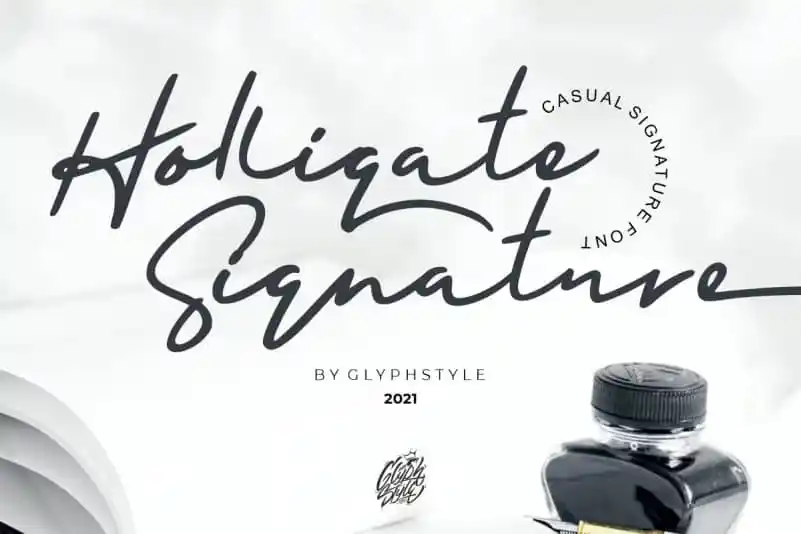
Holligate Signature Font – Fonte Grátis
Holligate Signature Font
A Holligate Signature Font é uma letra que desvenda a espiritualidade dos autógrafos relaxados e naturais. Suave e elegante, essa fonte traz uma sensação quase mágica de autenticidade à sua identidade visual. Com traços naturais, esta escolha perfeita para eventos como casamentos, marcas de água e até mesmo para as entrevistas. Seja para criar um logo memorável em produtos ou para dar vida a um cartão de visita empresarial – você estará seguro de que está adicionando o toque personalizado que sua marca merece. O design cuidadoso da GlyphStyle garante que cada traço reflete a confiabilidade e a elegância inerentes à sua identidade visual.